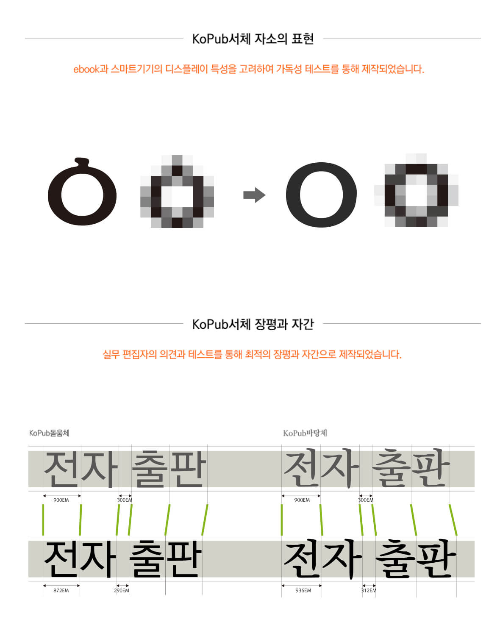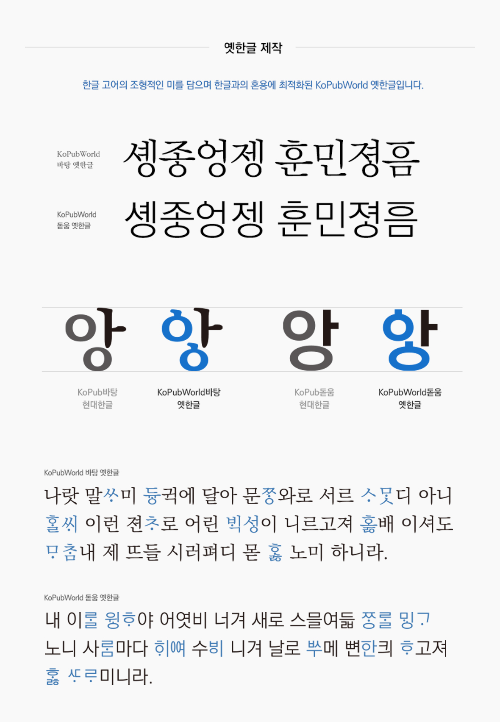
보고서나 발표자료를 책자로 만들어야 할 때는 Kopub 바탕/고딕체를 쓰세요
이번에 소개해 드릴 폰트는 Kopub 서체입니다. 한국출판인회의에서 출판물에 사용할 수 있도록 만들어 준 폰트입니다.
한글이나 파워포인트 발표자료에도 많이 이용하는 폰트이기도 합니다.
저도 책자를 만들어야 하는 보고서 자료나 외부에서 발표하는 자료에 이 폰트를 많이 사용하고 있습니다.
저는 주로 Kopub돋움체를 사용합니다. 바탕체는 명조체 느낌이 나서 더 예스럽고 돋움체는 좀 더 깔끔한 느낌이 나는 폰트이기 때문입니다. 마지막까지 포스팅을 읽으시면 활용팁도 있으니 끝까지 잘 보고 활용하시면 좋을 것 같습니다.
책자나 발표자료에 쓰실 폰트가 필요하시다면 이 폰트를 사용하시면 됩니다.
Kopub 체를 활용하는 팁
그리고 한가지 팁이 더 있습니다.
한글 이외에 영어나 외국어를 써야 할 때는 Kopub World 체를 이용하시는 것이 좋습니다.
Kopub체는 한글을 중심으로 만들어져 있기 때문에 한글을 쓸 때는 깔끔하게 잘 나옵니다.
그리고 외국어를 섞어야 하고 빈도가 높은 자료에는 Kopub World체로 사용하시면 좋습니다.